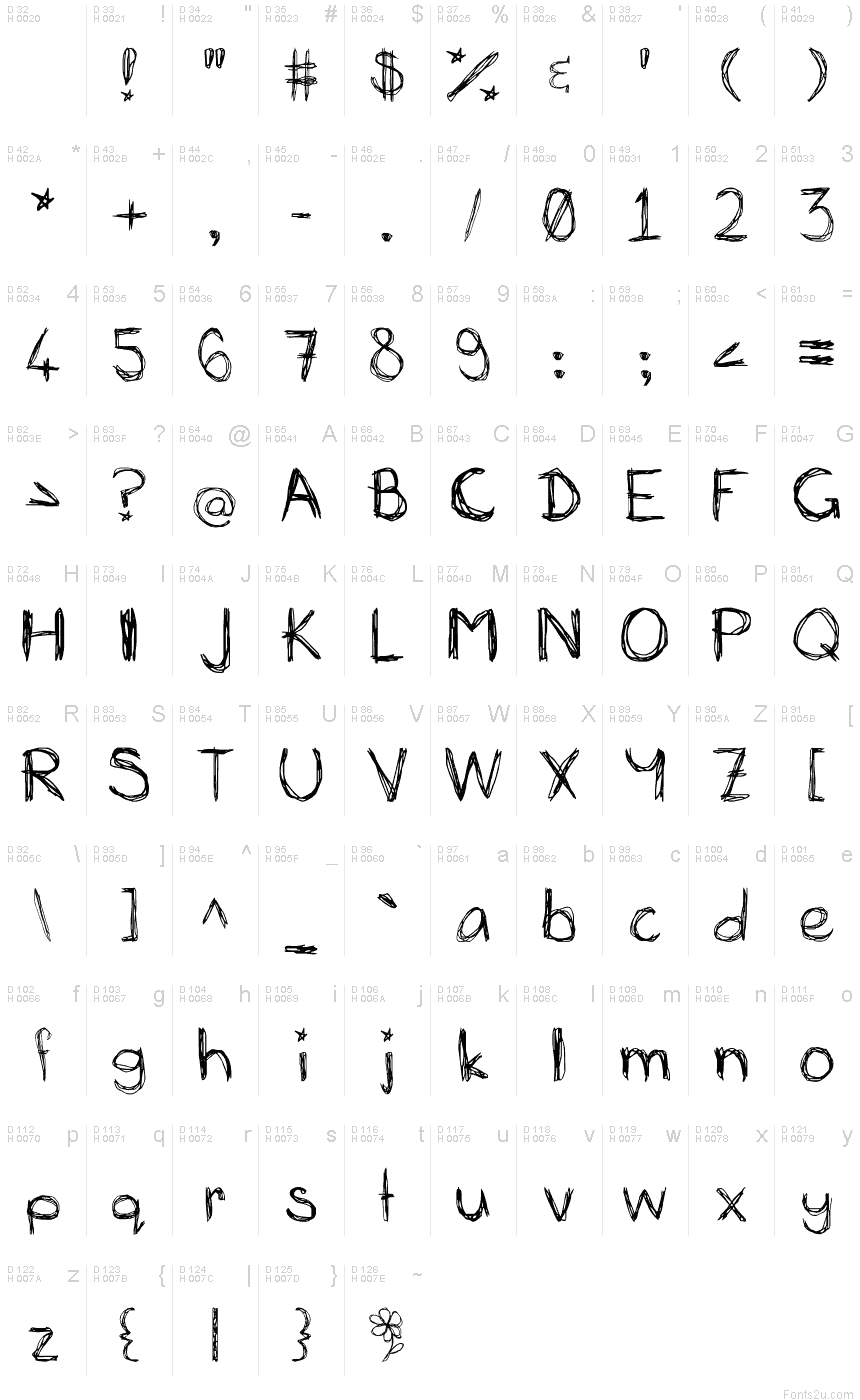
Mia's Scribblings ~ TrueTypeFreeware
Mia's Scribblings to darmowy, odręczny font w stylu luźnego, artystycznego szkicu. Litery wyglądają jak szybko nabazgrane grubym markerem – pełne niespokojnych nakładek, nierównych pociągnięć i naturalnych krzywizn, dzięki czemu cały font sprawia wrażenie notatek na marginesie, a nie dopracowanego liternictwa.
Świetnie pasuje do ulotek, okładek zinów, stron scrapbookingu, nagłówków plakatów czy kartek w stylu pamiętnika, gdzie ten chaotyczny, osobisty ton pomaga przekazać komunikat. Jako darmowy font, sprawdzi się również w krótkim brandingu, grafikach na bloga czy wyróżnieniach, gdy potrzebujesz liter, które wydają się impulsywne, nieco surowe i wyraźnie rysowane ręcznie.